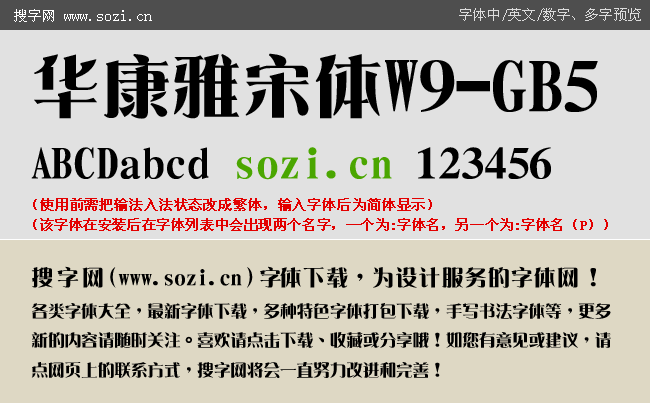
華康雅宋體W9簡(jiǎn)體
搜字網(wǎng)提供一款華康雅宋體藝術(shù)字體下載,華康雅宋體以宋體的基礎(chǔ)上加以美化,筆畫(huà)處修以花邊,轉(zhuǎn)折處稍微圓潤(rùn),相比棱角分明的宋體,又多了一分可親近的感覺(jué)。該字體端正大方,且結(jié)構(gòu)清晰、風(fēng)格統(tǒng)一,適合海報(bào)設(shè)計(jì)、畫(huà)冊(cè)設(shè)計(jì)、廣告宣傳設(shè)計(jì)等領(lǐng)域。